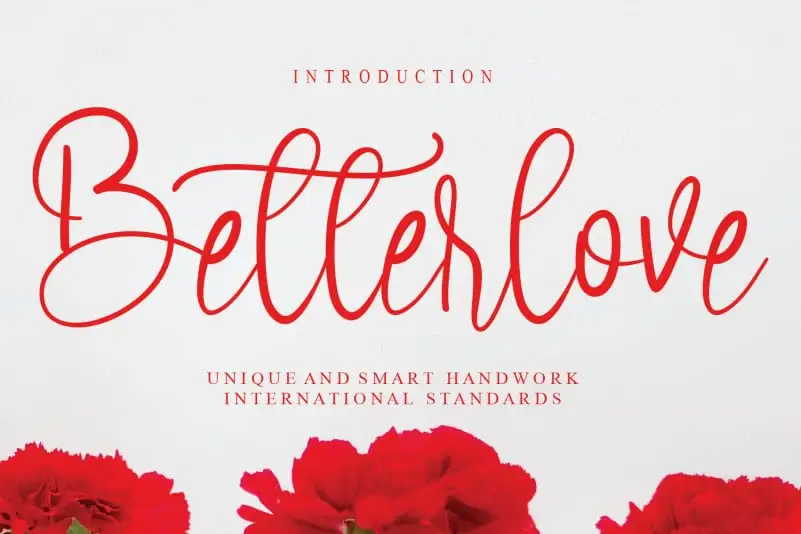
Betterlove Calligraphy Font – Download Grátis
Através do ‘Betterlove Calligraphy Font’, criado pelo designer creativeletter, você mergulha num universo de expressões artísticas que vão além das palavras tradicionais. Esta categoria de fontes script é uma ferramenta revolucionária para artistas e profissionais da comunicação visual, oferecendo uma experiência única de escrita com um toque único de criatividade. Com linhas sutis e traços elegantes que expressam a alma do texto através de cada letra, esta fonte permite ao usuário criar mensagens que não só são visíveis, mas também vibrantes. Ela é perfeita para aqueles que desejam dar vida à sua escrita, seja em um livro infantil encantado ou em uma carta emocionante de amor. Ao adquirir ‘Betterlove Calligraphy Font’, você tem a oportunidade de expressar seus sentimentos de maneira única e profunda, criando obras de arte que vão além da palavra, trazendo vida para o papel. Este é mais do que simplesmente uma ferramenta de escrita: ele abre as portas para um novo nível de expressão artística. Tudo isso sob a promessa especial e criativa do designer creativeletter, garantindo que você tenha um experiência única e extraordinária ao usar esta fonte.